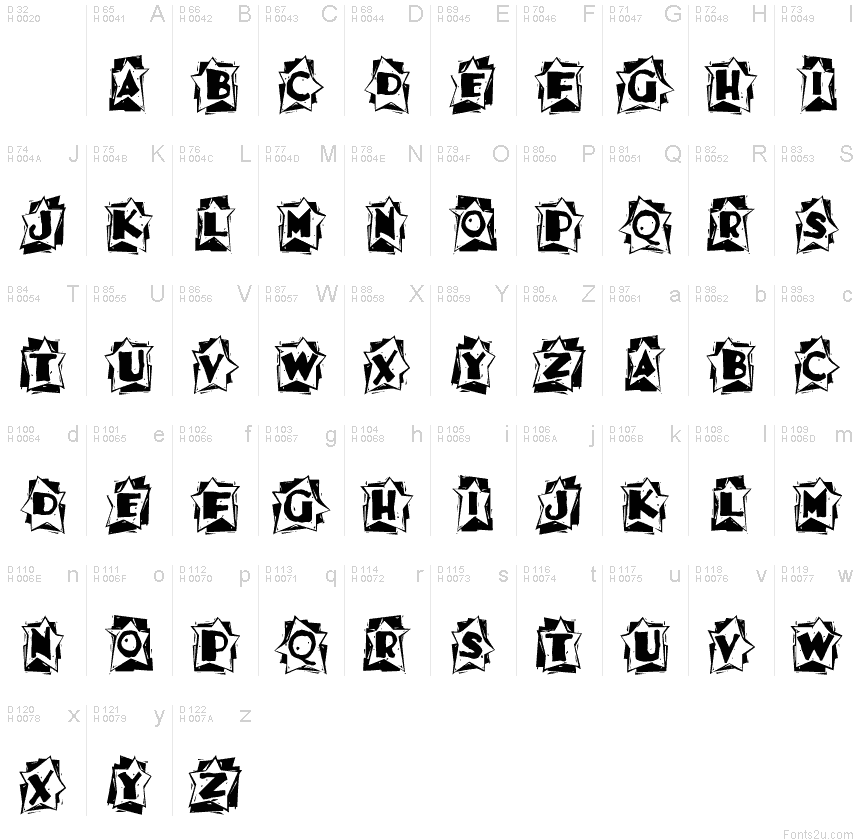
Font A Star is Born autorstwa Melle DERIEPPE Claude to darmowy, dekoracyjny krój typu display, który wygląda, jakby dopiero co wyskoczył z wielkiego neonu. Każda litera jest zamknięta w poszarpanym, ręcznie rysowanym obrysie gwiazdy, wypełniona głęboką czernią i ostrymi, białymi akcentami – całość jest głośna, błyszcząca i w najlepszym tego słowa znaczeniu nieco chaotyczna. Ten wyrazisty, gotowy do druku na plakatach font przykuwa uwagę z drugiego końca pomieszczenia i nie pozwala o sobie zapomnieć.
Zastosowanie A Star is Born nadaje każdemu projektowi energię „wielkiej premiery”, dzięki czemu jest to naturalny wybór na plakaty konkursów talentów, zaproszenia na imprezy dla dzieci, branding cyrków czy karnawałów, okładki komiksów, miniatury na YouTube czy ulotki imprez muzycznych. Ten darmowy font najlepiej sprawdza się w dużych, śmiałych rozmiarach, gdzie kolczaste kształty gwiazd mogą w pełni zaprezentować swój urok; połącz go z czystym, neutralnym fontem bezszeryfowym w tekście głównym, aby zachować czytelność projektu, podczas gdy nagłówek skradnie całą uwagę.